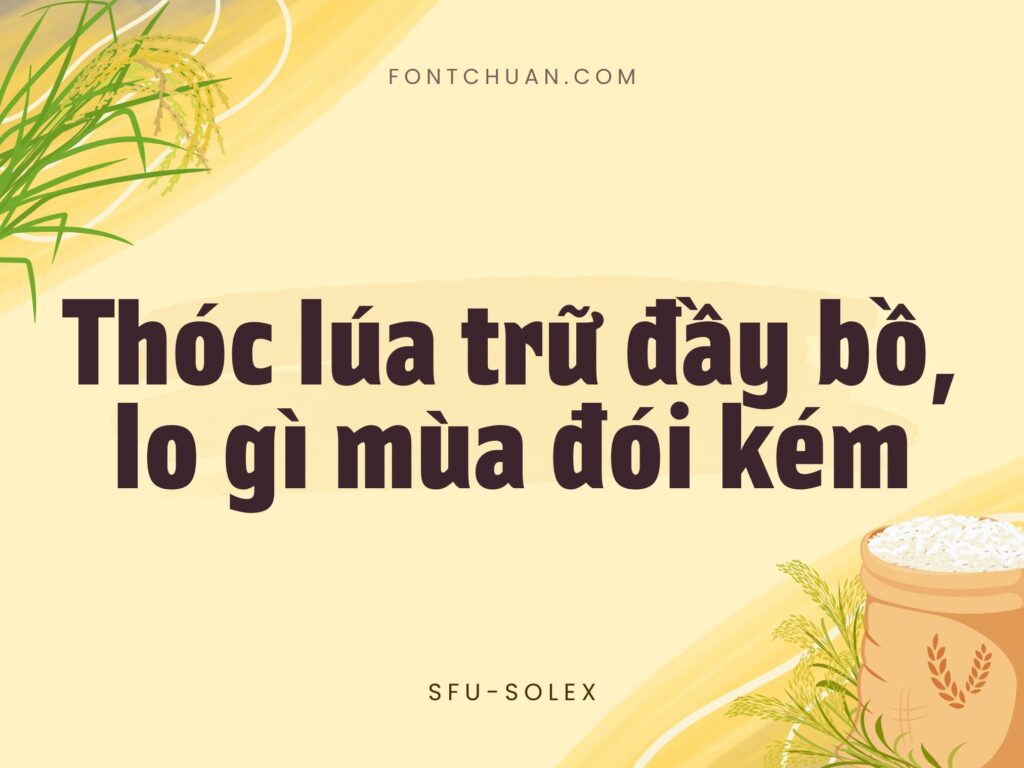
Font SFU Solex Việt Hóa
Font SFU Solex Regular là một kiểu chữ sans-serif công nghiệp hiện đại, được thiết kế bởi Zuzana Licko từ Emigre. Font này kết hợp các ý tưởng từ nhiều giai đoạn phát triển khác nhau trong hơn một thế kỷ qua, lấy cảm hứng từ các kiểu chữ như Alternate Gothic (1903), Standard Gothic (1896) và News Gothic (1908). Solex nổi bật với thiết kế chữ hẹp, hình chữ nhật và các đặc điểm độc đáo như serif ở chân và đầu một số ký tự, tạo nên sự kết hợp giữa phong cách công nghiệp và tính dễ đọc.
SFU Solex Regular lý tưởng cho các dự án thiết kế logo, tiêu đề, bao bì sản phẩm và các ấn phẩm quảng cáo. Các ngành nghề như quảng cáo, giáo dục và công nghệ có thể tận dụng font này để tạo điểm nhấn trong thiết kế. Ngoài ra, font cũng thích hợp cho các sự kiện như Tết, Giáng sinh, Valentine và các lễ hội khác.